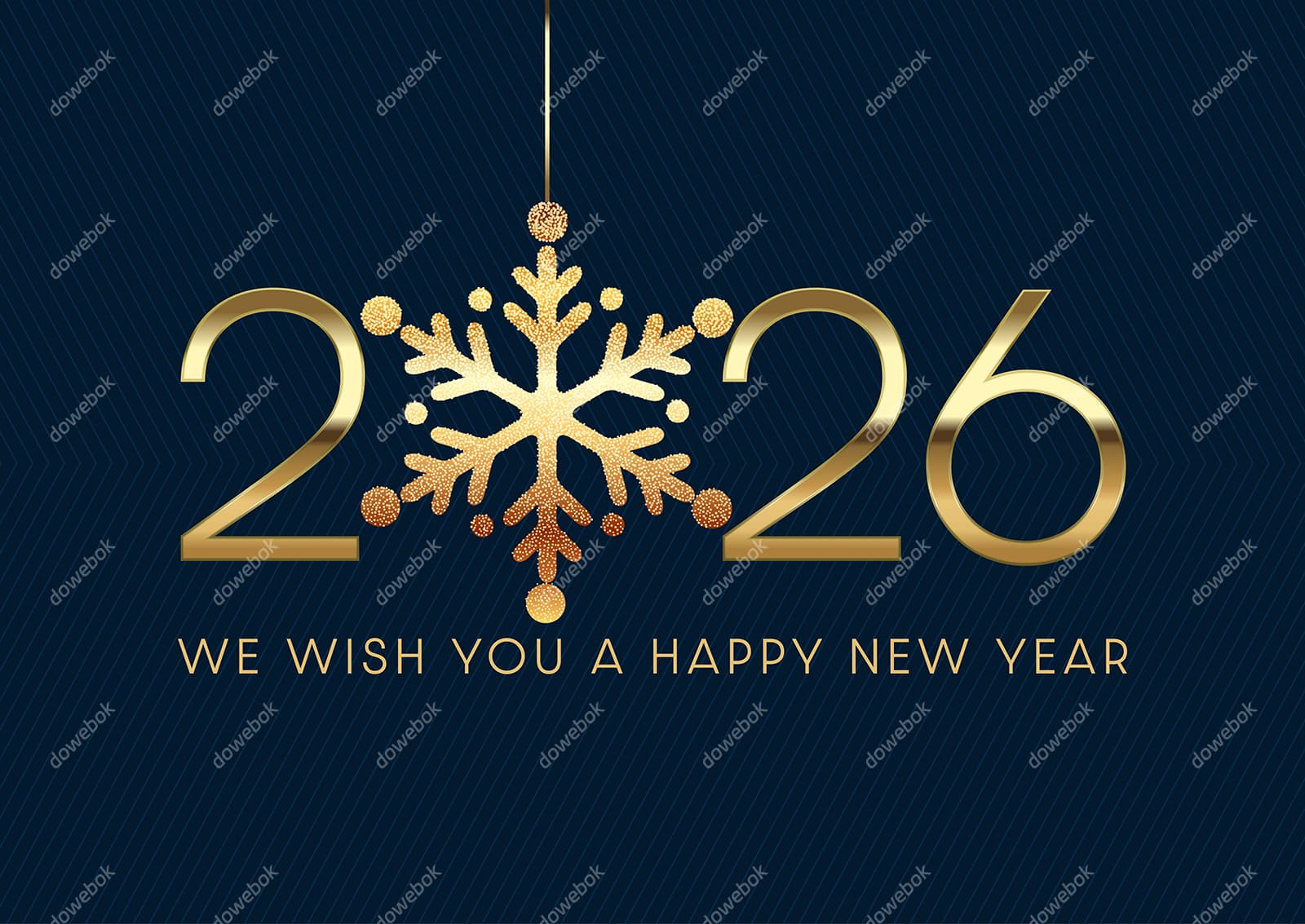
这是一款金色雪花和数字设计的 2026 新年快乐矢量素材,藏蓝暗纹背景沉稳雅致,鎏金 “2026” 字体间嵌着带珠饰的雪花挂饰,似节日吊饰灵动精致。下方 “WE WISH YOU A HAPPY NEW YEAR” 字样同色呼应,整体以蓝金配色融合冬日雪花元素,既显跨年的轻奢格调,又用挂饰细节透出温馨的节日仪式感,沉稳中不失精致氛围。